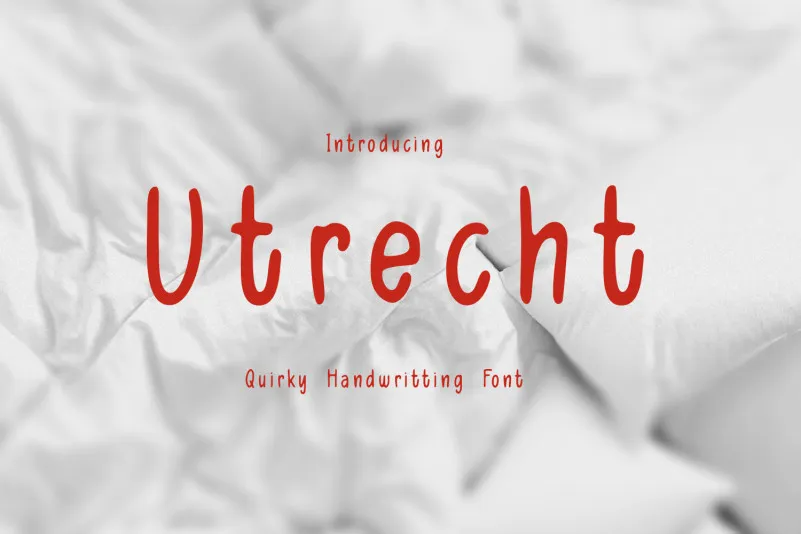
Utrecth Script Font – Fonte Grátis
Utrecth Script Font
A fonte Utrecth Script é uma escrita casual que captura a essência do estilo livre e informal dos textos manuscritos. Ela não se limita apenas às palavras, mas também à maneira como elas são escritas. Esta fonte é perfeitamente adaptada para uso em design gráfico pessoal ou corporativo, oferecendo um toque único que torna os projetos mais interessantes e memoráveis. A 38.lineart foi responsável por desenvolver este estilo inovador que abrange mais de 24 idiomas, proporcionando uma variedade incrível de possibilidades. Utrecth Script é ideal para aqueles que desejam adicionar um elemento único ao seu design, seja em logotipos, materiais promocionais ou até mesmo no próprio website. A fonte mantém a essência da escrita manuscrita em cada característica, tornando-a versátil e adaptável aos mais diversos contextos.